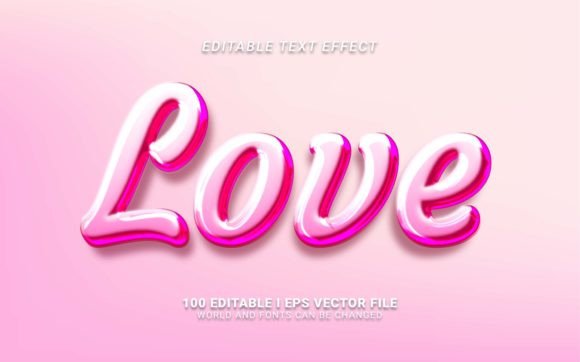
Love Text Effect
Được chế tác với độ chính xác cao, Love Text Effect cung cấp các vector sạch, kiểu chữ mượt mà và giấy phép thương mại để bạn yên tâm.